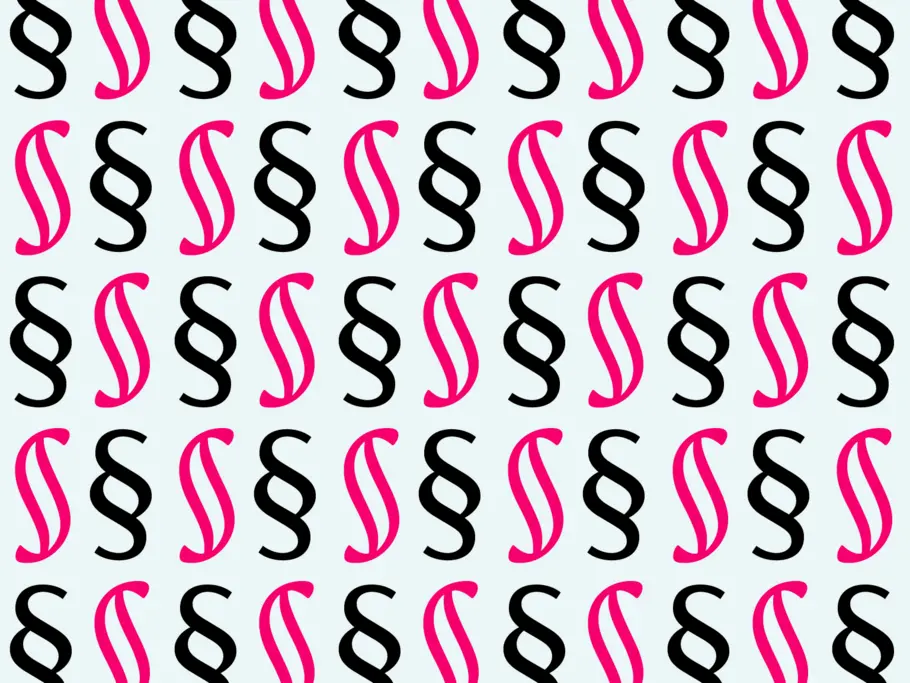
Zeichenlehre: Das Paragrafzeichen §
Das Paragrafzeichen, Paragrafenzeichen oder auch Abschnittzeichen ist ein Sonderzeichen, das in Gesetzestexten einer Zahl vorangestellt wird und den Beginn eines neuen Paragrafen (= Absatz) anzeigt, der durch die Zahl bezeichnet wird: § 130 StGB.  Seine Form leitet sich von einem doppelten s ab, das im Lateinischen für signum sectionis, also Abschnittszeichen steht. Ab dem 16. Jahrhundert ist die konkrete Anwendung des Paragrafzeichens in deutschen Rechtstexten belegt.
Das Symbol hat sich aus historischen Schriften entwickelt. Da Papier früher sehr kostbar war, sparten sich die Schreiber das Einfügen einer neuen Zeile am Ende eines Absatzes: Sie setzten das Absatzzeichen als Trennung ein (auch signum separandi). Es wurde als gekoppeltes ss geschrieben. Die handschriftliche Ausführung führte über Jahrhunderte zu vielen verschiedenen Formen des §.
Diese Vielfalt hat sich in der typografischen Praxis erhalten, sodass Schriftgestalterinnen und -gestalter die Möglichkeit hat, damit zu spielen. Die obige Abbildung zeigt zwei stark abweichende Versionen aus den Schriften FS Siena (schwarz) und FS Brabo (rot). Auch wenn es auf einem Doppel-s basiert, muss sich das Paragrafzeichen als Symbol vom Buchstaben s klar abheben.
Es kann Spaß machen, das Zeichen zu entwerfen, es kann aber auch zum Albtraum werden. Wer schon einmal eine Schrift entworfen hat, weiß, dass es eine große Herausforderung ist, die richtige Form des Buchstaben s zu finden. Und dann kommt irgendwann das Paragrafzeichen, was doppelt schwierig ist, denn es gilt zwei s zusammenzubauen und zu einem harmonischen Zeichen zu entwickeln. Gute Typedesigner schenken jedem Zeichen in ihren Schriften eine hohe Aufmerksamkeit, auch solchen, die nicht täglich zum Einsatz kommen. Beim Paragrafzeichen vergehen manchmal Tage, bis man als Entwerfer damit zufrieden ist.
Das § kommt in Deutschland ständig zum Einsatz, weil es fester Bestandteil der Bundes- und Landesgesetze ist. International hat sich die Einteilung der Gesetze in Artikel durchgesetzt, wie auch im Grundgesetz der Bundesrepublik oder in bayerischen Landesgesetzen. Wenn hierzulande Gesetze in den Medien oder in Korrespondenzen zitiert werden, geschieht dies mit dem Paragrafzeichen.
Beispiel: Bürgerliches Gesetzbuch § 437
Nach dem Abschnittszeichen folgt eine Nummer, daher ist es ratsam, direkt danach ein geschütztes Leerzeichen zu setzen, damit das Symbol und die Nummer nicht auf zwei verschiedenen Zeilen stehen. Wenn sich ein Text auf mehrere Paragrafen beziehen, wird das Zeichen doppelt geschrieben:
Beispiel: nach den §§ 440, 323 und 326 Abs. 5
In seltenen Fällen kann es verwendet werden, um auf eine Fußnote zu verweisen, wenn das Sternchen*, das Kreuz † und das Doppelkreuz ‡ bereits auf einer Seite im Einsatz sind.
Trivia: Eine modifizierte Version des Abschnittszeichens wird im Videospiel Die Sims als Symbol für die fiktive Währung Simoleon verwendet.